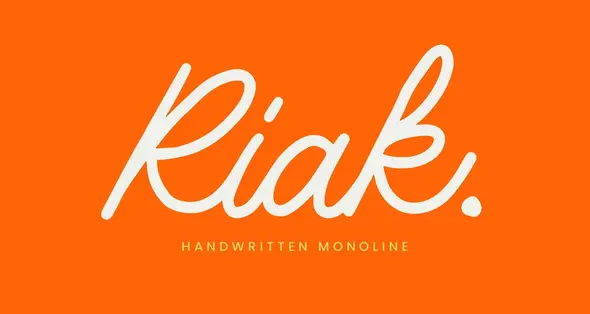
• Riak Handwritten Monoline Font
فونت انگلیسی دست نویس
• circle سبک قلم: مونولاین
• circle حروف کوچک
• circle حروف بزرگ
• circle علائم نگارشی
• circle پشتیبانی زبان‌ها
Riak یک فونت مونولاین دست‌نویس روان و شیک است که جلوه‌ای شخصی و ظریف به کارهای خلاقانه شما می‌بخشد. با منحنی‌های سیال و ضخامت خط یکنواخت، Riak جذابیت دست‌خط طبیعی را به تصویر می‌کشد در عین حال ظاهری تمیز و حرفه‌ای را حفظ می‌کند. این فونت ایده‌آل برای زیبایی‌شناسی سرگرم‌کننده، غیررسمی و چشم‌نواز، و گرافیک شبکه‌های اجتماعی است.
Riak که برای بیانگر بودن و تطبیق‌پذیری طراحی شده است، شامل مجموعه‌ای کامل از حروف بزرگ و کوچک، اعداد و علائم نگارشی است. چه در حال کار بر روی یک هویت بصری مینیمالیستی باشید و چه یک پیام صمیمانه، این فونت به زیبایی با پروژه‌های چاپی و دیجیتال سازگار می‌شود.
با Riak، حس گرما و پیچیدگی را به طراحی خود اضافه کنید. فونتی که سادگی ساختار مونولاین را با روح خط دست‌نویس ترکیب می‌کند.
Riak Handwritten Monoline Font
Riak is a smooth and stylish handwritten monoline font that brings a personal, elegant touch to your creative work. With its fluid curves and consistent stroke weight, Riak captures the charm of natural handwriting while maintaining a clean, professional look— perfect for a fun, informal, and eye-catching aesthetic, and social media graphics.
Designed to be both expressive and versatile, Riak comes with a full set of uppercase and lowercase letters, numerals, and punctuation. Whether you're working on a minimalist brand identity or a heartfelt message, this font adapts beautifully to both print and digital projects.
Add a sense of warmth and sophistication to your design with Riak—a font that blends the simplicity of monoline structure with the soul of hand-drawn script.
- Smooth monoline stroke
- Uppercase & lowercase letters
- Numbers (0–9)
- Basic punctuation
- Multilingual support